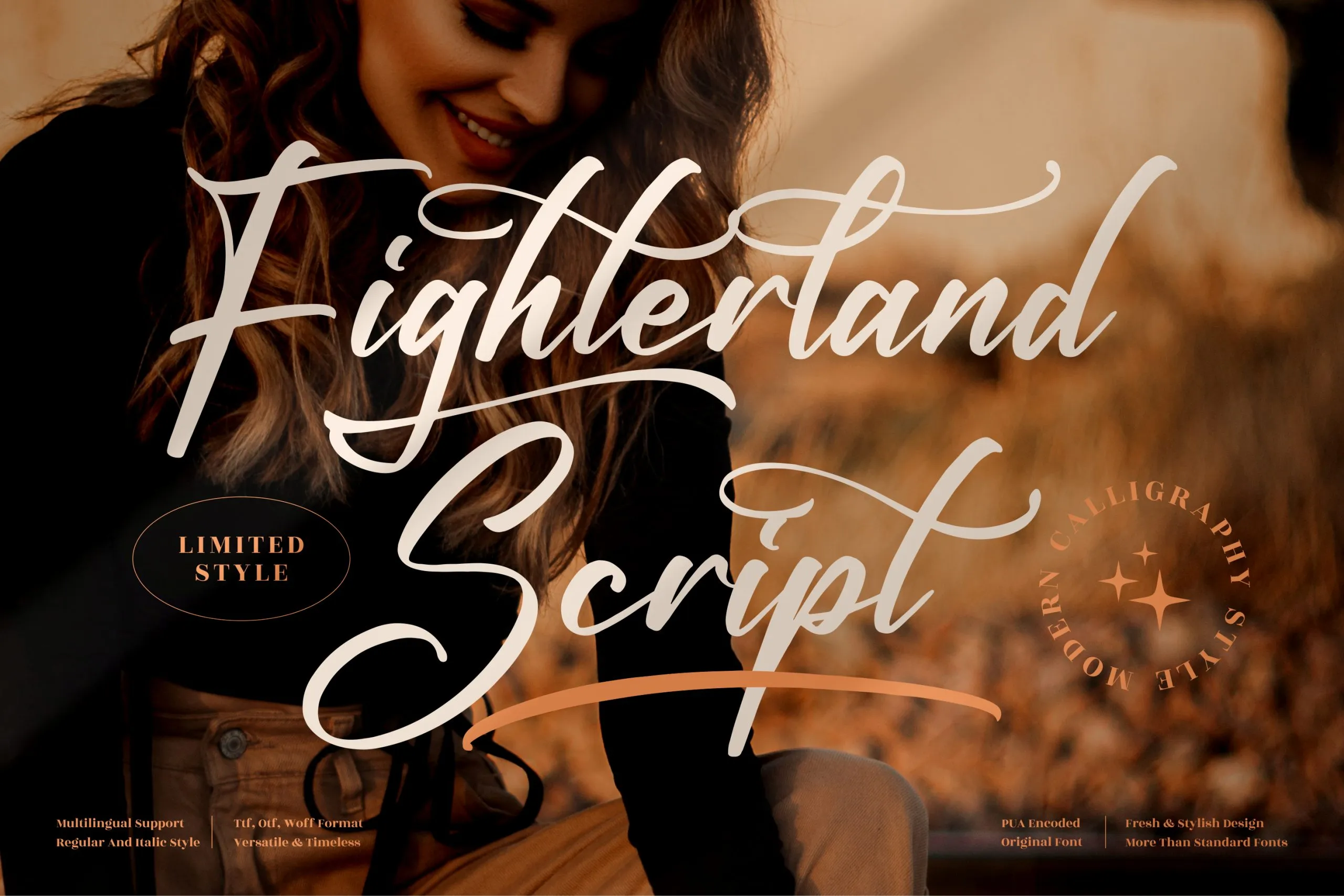
A Fighterland Script Font é uma elegante tipografia que traz a sofisticação do gótico moderno para qualquer projeto gráfico. Desenvolvida pela Perspectype Studio, esta fonte premium oferece um toque de luxo e refinamento que se destaca em diversas aplicações. Seja para criar um logotipo impressionante, desenvolver uma identidade visual única ou até mesmo personalizar etiquetas para produtos, a Fighterland Script é o elemento perfeito para dar um toque de elegância. Perfeita para designs de marcas e cartões de visita, adesivos de festa, caixas de embalagem, capas de livros, estandartes de eventos especiais ou qualquer outro projeto que busca uma aparência premium e sofisticada. Esta fonte é ideal para quem procura por um toque personalizado de alta qualidade, seja para uso pessoal ou profissional.